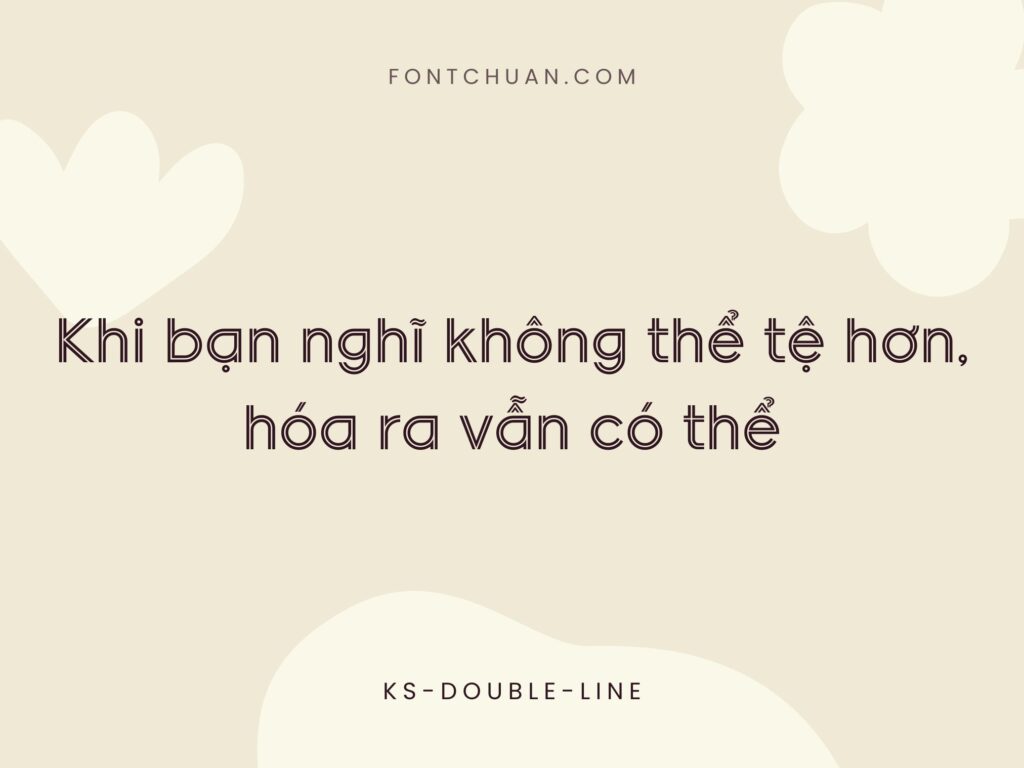
Font Ks Double Line Việt Hóa
KS Double Line là một phông chữ độc đáo thuộc loại Font Display, với thiết kế gồm hai đường kẻ song song, tạo nên sự mới lạ và phong cách cho các dự án thiết kế. Được ra mắt vào năm 2000 bởi đội ngũ K-Type, phông chữ này đã nhanh chóng thu hút sự chú ý nhờ khả năng sáng tạo và tính ứng dụng đa dạng. Phiên bản KS Double Line đã được Việt hóa hoàn toàn, hỗ trợ đầy đủ các ký tự tiếng Việt, giúp người dùng Việt Nam trải nghiệm gõ chữ trọn vẹn và dễ dàng tích hợp vào các thiết kế địa phương. Ngoài tiếng Việt, phông chữ này còn hỗ trợ nhiều ngôn ngữ khác, mở rộng khả năng ứng dụng trong các dự án quốc tế. Việc Việt hóa được thành viên của Font Chuẩn chọn lọc và sưu tầm nhằm đáp ứng nhu cầu bạn đọc và ứng dụng thực tế vào các dự án thiết kế.
Về đặc điểm thiết kế, KS Double Line thuộc loại phông chữ sans serif với cấu trúc chữ cái gồm hai đường kẻ song song, tạo nên hiệu ứng thị giác độc đáo. Độ tương phản thấp và độ dày đồng đều giúp phông chữ trở nên dễ đọc ở các kích thước khác nhau. Các ligature được thiết kế tinh tế, tạo sự liền mạch và thẩm mỹ cao cho văn bản. Với những đặc điểm trên, KS Double Line phù hợp cho các ứng dụng như thiết kế logo, tiêu đề, bao bì sản phẩm và các dự án sáng tạo khác. Phông chữ này cũng thích hợp cho các thiết kế cần sự độc đáo và hiện đại, như áp phích quảng cáo, tạp chí và các sản phẩm thương hiệu. Về ngành nghề, KS Double Line đặc biệt phù hợp với lĩnh vực quảng cáo, công nghệ, giáo dục và các ngành nghề cần sự sáng tạo và hiện đại trong thiết kế. Sự linh hoạt và tinh tế của phông chữ giúp nó dễ dàng hòa nhập vào nhiều phong cách thiết kế khác nhau, từ cổ điển đến hiện đại.